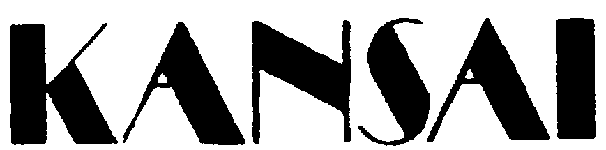
Broadway Lookalike
heute habe ich auch mal eine Anfrage zu einer unbekannten Schrift:
Ich habe leider nur diesen ausgefransten Scan, aber vielleicht klingelt es ja bei jemandem. Broadway denkt man auf den ersten Blick – die ist es aber nicht. Binner auch nicht.
Aber welche dann?
Ist das eine Wortmarke bzw. Teil eines Logos?
Ja, ist es.
Aber die haben keine saubere Vektorgrafik davon und ich bezweifle auch, dass das von Hand gezeichnet wurde.
Vielleicht aus der Snip Tuck und der Broadway zusammengefummelt … oder auf irgendeiner CorelDraw-CD, was ich noch eher glaube.
vom gefühl her sieht das irgendwie nach corel draw aus ... nur leider habsch kein corel mehr mit zugehöriger fontsammlung.
inzwischen ist es auch schon fast egal, weil ich das teil schon nachgebastelt habe, aber interessieren würde es mich doch, was das für ein font ist.